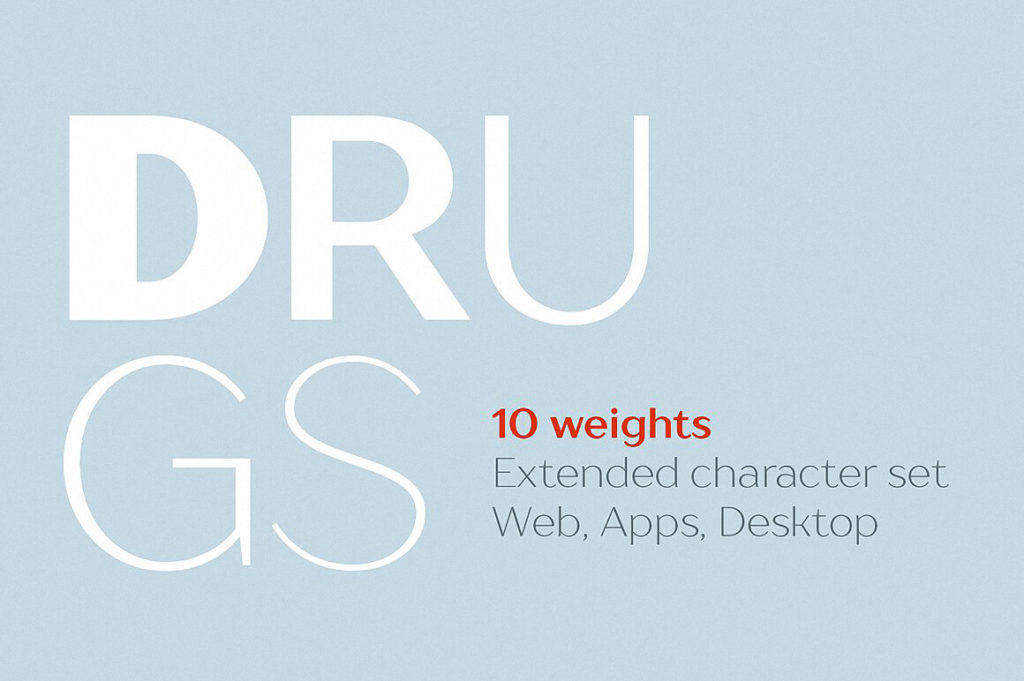
Шрифт TT Drugs
Это выразительный гротеск от студии TypeType, восходящий к оригинальным работам Питера Вигеля. Он выделяется высокой контрастностью штрихов и изысканной геометрией, где узкие терминалы букв придают начертанию элегантный и слегка брутальный вид. Кириллическая версия профессионально адаптирована для набора текстов на русском языке, сохраняя уникальный дух оригинала. Этот кириллический шрифт отлично подходит для создания смелой айдентики, модных заголовков и акцидентной типографики. Вы можете скачать TT Drugs бесплатно для личных проектов; однако для коммерческого использования необходимо приобрести лицензию у правообладателя.